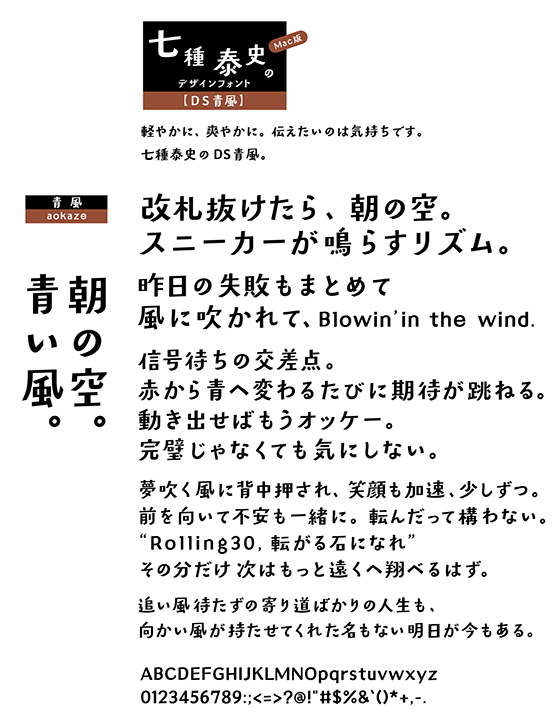
DS青風 (DS-aokaze)
DS-aokaze
さわやかな元気な青い風。力強さを感じさせる書体です。
七種泰史/デザインシグナルの紹介
こころのこもった文字創りを目指す七種泰史氏のオリジナルブランド「デザインシグナル」。2008年夏からスタートし、年に2~3書体のペースで開発を進行中。多くのファンが新作を心待ちにする人気のブランド。